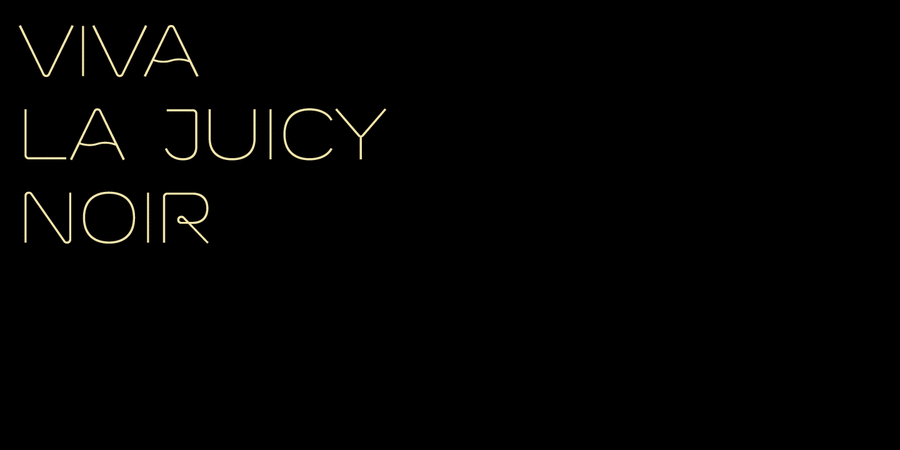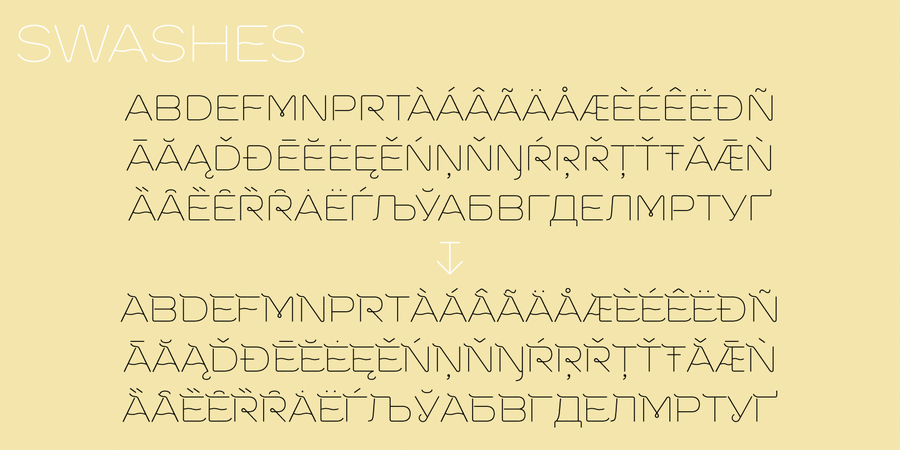
Vanyla 4F Unicase (2 шрифта)
Опис гарнітури Vanyla 4F UnicaseШрифт Vanyla 4F Unicase содержит 2 начертания и отлично подходит для рекламы, неоновых вывесок, журнальных заголовков и другой акциденции. Разработан Сергеем Ткаченко в 2013 году.
Асоціації з сімейством шрифтів Vanyla 4F UnicaseОсобистість і характер гарнітури:
неоновий, тусовочний, делікатний, плавний, чистий, легкий, прохолодний, свіжий, модний, міський, тонкий, сучасний, лаконічний, вільний, невагомий, прозорий, інтимний, клубний, гнучкий, гладенький, характерний, оригінальний, незвичайний, виразний, молодіжний, позитивний, артистичний, музичний, популярний, М'який, вигнутий, ніжний, повітряний, дротяний, гарненький, симпатичний, нічний, дівчачий, рухливий, динамічний, творчий
Місто, парфумерія, лосьйон, краса, туалетна вода, шампунь, косметика, мода, дієта, дизайн, гігієна, чистота, відпочинок, море, відпустка, кафе, бар, алкоголь, нічний клуб, розваги, атракціон, телебачення, кіно, кінотеатр, прикраса, пляж, інтер'єр, аксесуари, шоу, мюзикл, музика, естрада, перукарня, сукня, одяг, вечірка, тусовка, АСМР, коктейль, танець, дискотека, аквадискотека, йога Гарнітура асоціюється з віком: